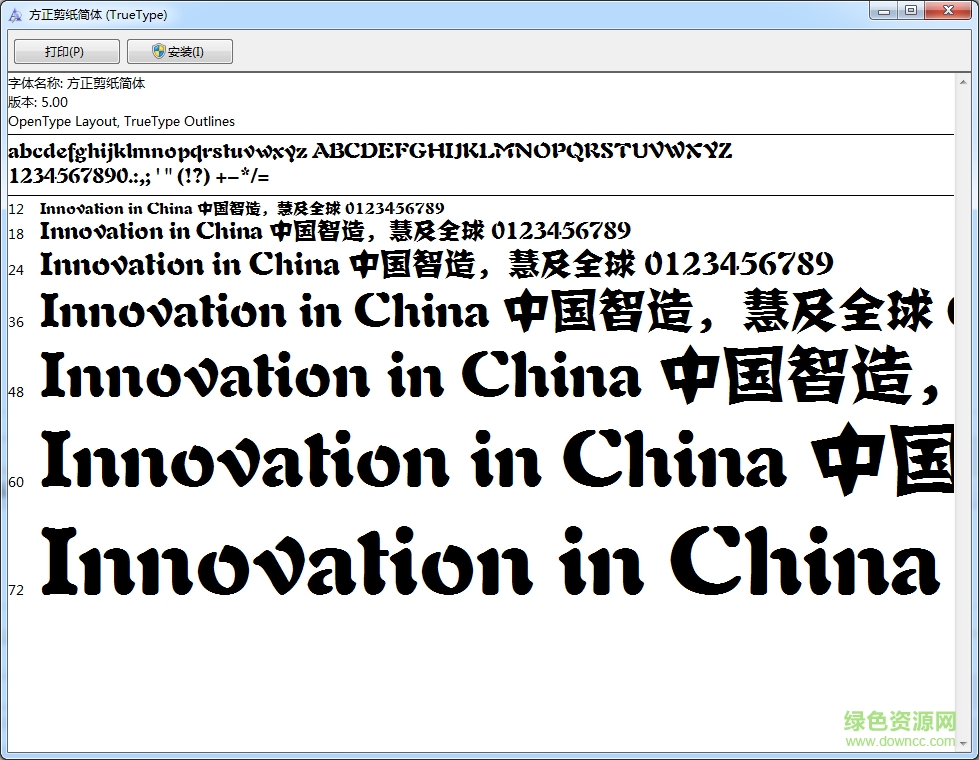
fzjzjw gb1 0字体是方正字体中第一款非常挺有特色的中文字体,格局中国传统的剪纸打造而来,非常的有特色,而且这款字体十分的好用,喜欢的朋友欢迎下载使用!
fzjzjw gb1 0字体也就是方正剪纸简体,是方正字库出品的一款中文字体,字体自带加粗效果,非常的醒目,适合用于广告设计和印刷包装行业!